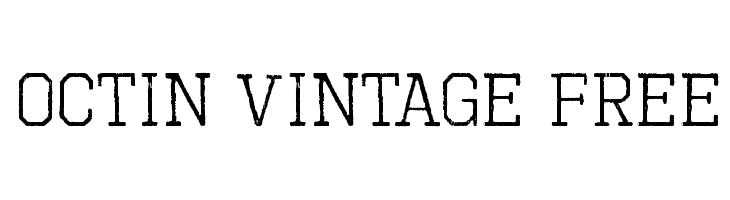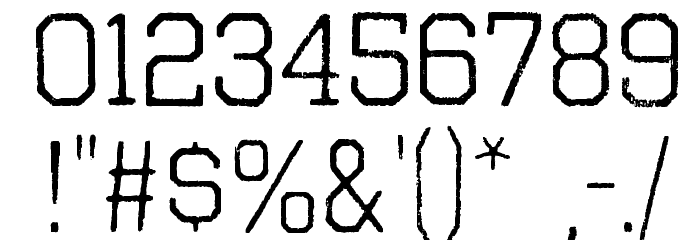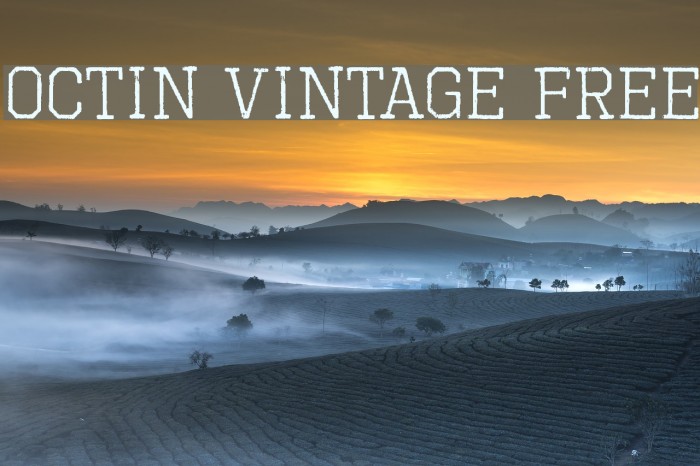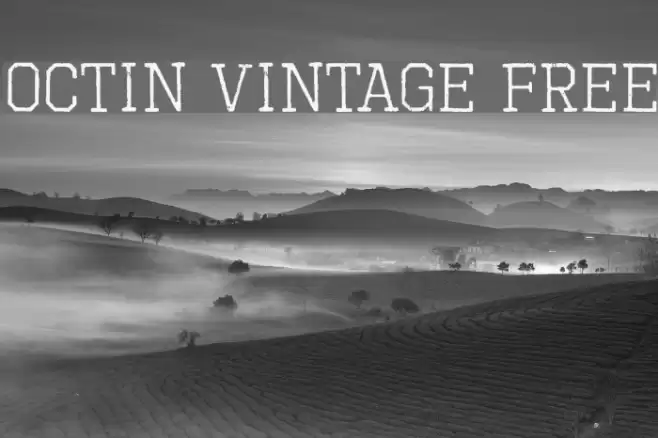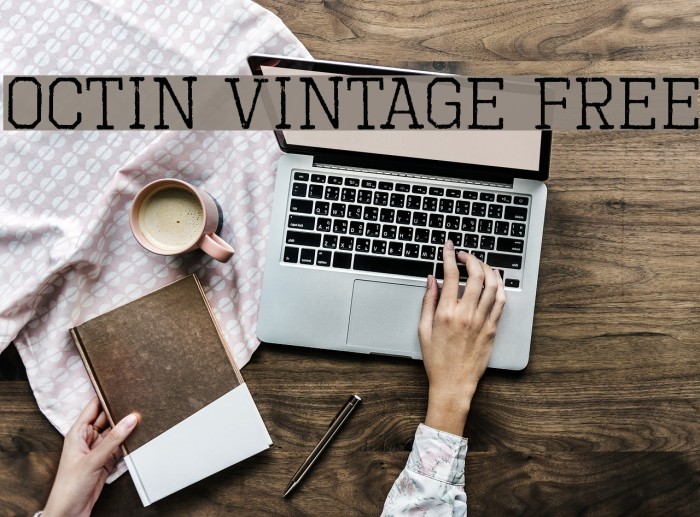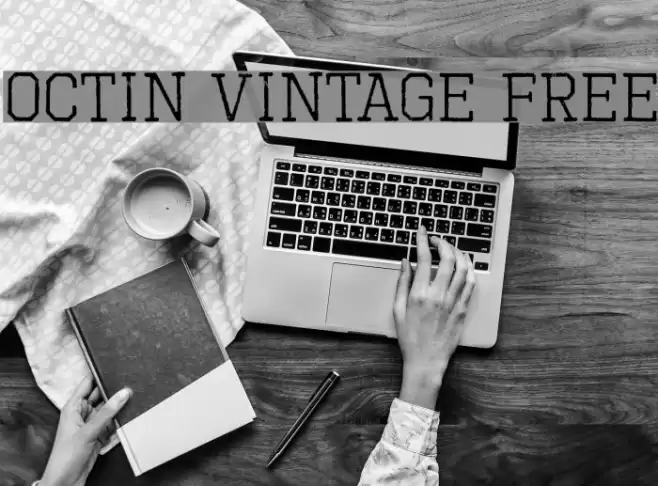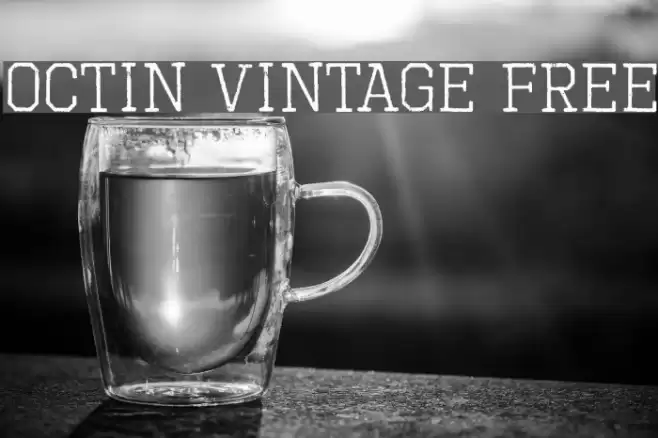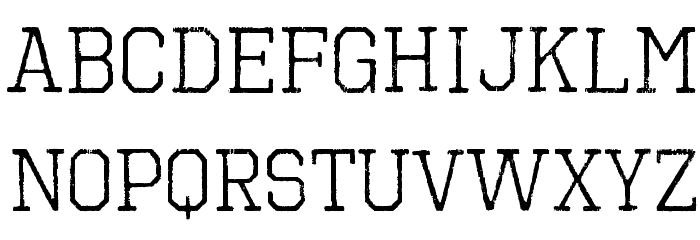
Octin Vintage Free Font
✎ Distorted Eroded
| Categorie | Distorted Eroded |
| Progetti proposti | Ideal for vintage-themed posters, industrial design projects, retro branding, and any creative work that requires a nostalgic touch. |